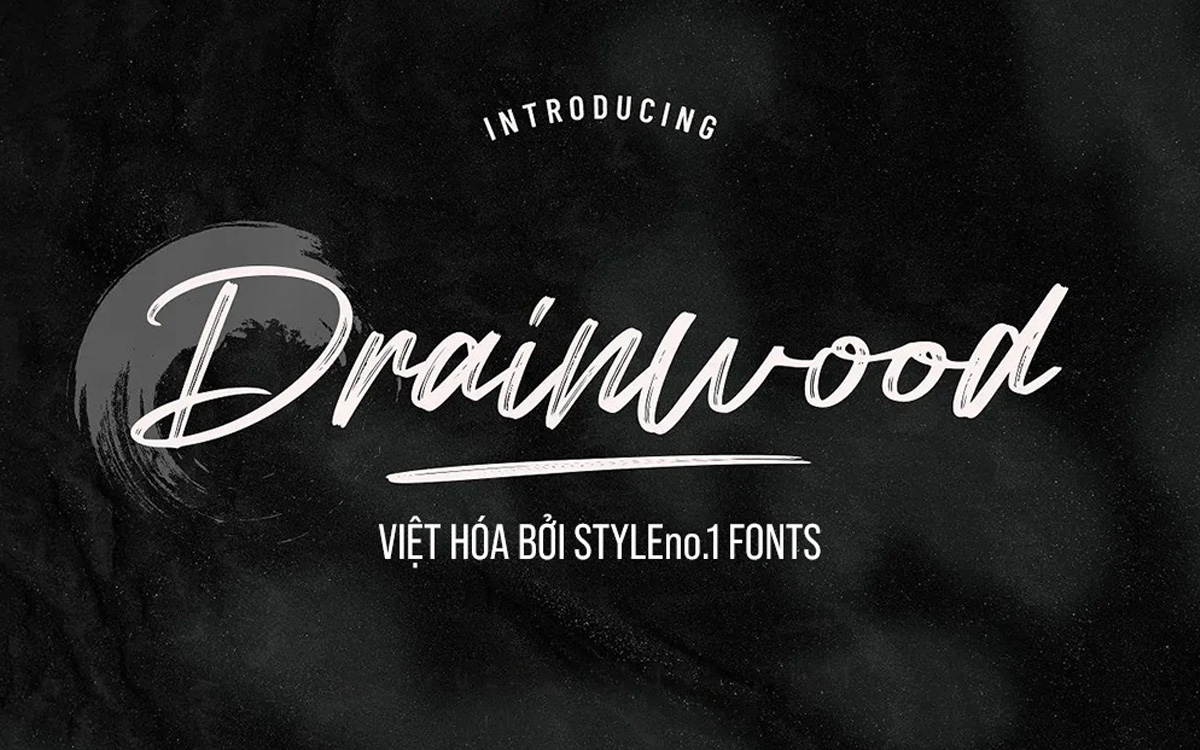
Font chữ nét cọ mềm mại viết tay SVN-Drainwood
Nếu bạn đang tìm kiếm một bộ phông chữ vừa mang phong cách nghệ thuật phóng khoáng, vừa giữ được sự mềm mại tự nhiên của nét cọ thủ công, thì font chữ nét cọ mềm mại viết tay SVN-Drainwood chính là sự lựa chọn hoàn hảo. Với các đường nét uốn lượn giàu cảm xúc cùng bản Việt hóa chỉn chu, bộ font này giúp nâng tầm những ý tưởng thiết kế truyền thông, nhận diện thương hiệu hay ấn phẩm in ấn trở nên vô cùng sống động. Hãy cùng khám phá chi tiết những đặc điểm nổi bật và tính ứng dụng vượt trội của phông chữ này ngay dưới đây.
Font Chữ Nét Cọ Mềm Mại Viết Tay SVN-Drainwood – Điểm Nhấn Nghệ Thuật Độc Đáo Cho Mọi Thiết Kế
Trong thế giới thiết kế đồ họa hiện đại, sự lên ngôi của các phông chữ viết tay (handwritten brush script) đã mang đến một làn gió mới, giúp sản phẩm truyền thông thoát khỏi sự khô khan của các hình khối truyền thống. Font chữ nét cọ mềm mại viết tay SVN-Drainwood không chỉ đơn thuần là một công cụ gõ vần mà còn là một tác phẩm nghệ thuật thu nhỏ, tái hiện chân thực từng cú nhấp cọ, từng vết loang mực nhè nhẹ của người nghệ sĩ typography. Bộ font này mang lại cho người xem cảm giác thân thiện, mộc mạc nhưng không kém phần tinh tế và sang trọng.
1. Đường Nét Cọ Viết Tay Tự Nhiên Và Giàu Cảm Xúc
Đặc trưng lớn nhất của font SVN-Drainwood chính là cấu trúc nét chữ được mô phỏng từ cọ vẽ thực tế. Các nét thanh, nét đậm được phân bổ vô cùng nhịp nhàng, tạo ra sự chuyển động thị giác mượt mà và ngẫu hứng. Không giống như nhiều bộ font script vi tính hóa khác có phần cứng nhắc, SVN-Drainwood giữ trọn vẹn sự gồ ghề nhẹ nhàng của vết mực, mang đến cảm giác chân thực, ấm áp và giàu chất thơ cho mọi tác phẩm thiết kế.
Mỗi ký tự trong bộ phông này đều được trau chuốt kỹ lưỡng để khi đứng cạnh nhau, chúng tạo nên một nhịp điệu liên kết tự nhiên như được viết ra trực tiếp từ bàn tay của một họa sĩ calligrapher chuyên nghiệp.
2. Hỗ Trợ Tiếng Việt Đầy Đủ Và Chuẩn Xác (Bản Việt Hóa Tỉ Mỉ)
Một trong những điểm cộng lớn khiến font chữ nét cọ mềm mại viết tay SVN-Drainwood được cộng đồng designer Việt Nam cực kỳ ưa chuộng chính là khả năng hỗ trợ tiếng Việt trọn vẹn. Bản Việt hóa do SVN thực hiện được tính toán kỹ lưỡng về mặt khoảng cách (kerning) và vị trí của các dấu thanh như sắc, huyền, hỏi, ngã, nặng hay các dấu mũ.
Các dấu câu tiếng Việt không bị lệch hàng, không đè lên nét chữ chính hay làm mất đi vẻ thẩm mỹ vốn có của nét cọ. Nhờ đó, bạn hoàn toàn có thể yên tâm sáng tạo các nội dung tiếng Việt dài mà vẫn duy trì tính nghệ thuật cao nhất cho tổng thể bức ảnh.
3. Bộ Ký Tự Thay Thế (Alternates) Và Nét Nối (Ligatures) Phong Phú
Để tăng khả năng tùy biến cho nhà thiết kế, SVN-Drainwood tích hợp hệ thống OpenType Features mạnh mẽ với rất nhiều ký tự thay thế (Alternate Characters), nét uốn móc (Swashes) và nét nối (Ligatures). Điều này giúp bạn dễ dàng thay đổi điểm đầu, điểm cuối của một từ, tạo ra những logo hay tiêu đề độc bản không đụng hàng.
Việc kết hợp linh hoạt các nét uốn lượn này giúp cho tác phẩm của bạn trông hoàn toàn tự nhiên, xóa bỏ hoàn toàn cảm giác lặp lại ký tự thường thấy trên các ứng dụng máy tính.
4. Khả Năng Ứng Dụng Đa Dạng Trên Nhiều Lĩnh Vực Thiết Kế
Với vẻ đẹp vừa lãng mạn, vừa hiện đại, font chữ nét cọ mềm mại viết tay SVN-Drainwood có khả năng thích ứng tuyệt vời trên đa dạng các sản phẩm thiết kế đồ họa:
• Thiết kế bộ nhận diện thương hiệu: Tạo logo, nhãn mác, bao bì cho các sản phẩm handmade, mỹ phẩm thiên nhiên, quán cafe, tiệm bánh, hay thương hiệu thời trang vintage.
• Truyền thông mạng xã hội: Thiết kế banner, poster, hình ảnh câu nói hay (quotes), thumbnail YouTube, hình ảnh bài đăng Facebook, Instagram thu hút sự chú ý nhanh chóng.
• Ấn phẩm sự kiện & Thiệp cưới: Làm thiệp mời cưới, menu tiệc, bảng đón khách (welcome board) mang phong cách rustic, mộng mơ và sang trọng.
• Bìa sách & Tạp chí: Phù hợp cho các tiêu đề sách văn học, tiểu thuyết, tạp chí phong cách sống, du lịch và ẩm thực.
5. Tương Thích Hoàn Hảo Với Mọi Phần Mềm Thiết Kế Hàng Đầu
Bí Quyết Phối Hợp Font SVN-Drainwood Để Tạo Nên Sản Phẩm Thiết Kế Ấn Tượng
Mặc dù font chữ nét cọ mềm mại viết tay SVN-Drainwood sở hữu sức hút rất lớn, việc áp dụng đúng nguyên lý thị giác sẽ giúp sản phẩm thiết kế của bạn trở nên ấn tượng và chuyên nghiệp hơn nữa. Dưới đây là một số lời khuyên hữu ích từ các chuyên gia thiết kế:
Tạo Sự Tương Phản Với Các Font Chữ Không Chân (Sans-Serif)
Vì SVN-Drainwood là một font script nét cọ uốn lượn nổi bật, bạn nên sử dụng nó cho các tiêu đề chính (Headings), từ khóa quan trọng hoặc các dòng slogan ngắn. Đối với phần văn bản nội dung (Body text), hãy kết hợp cùng các phông chữ không chân đơn giản như Montserrat, Helvetica, Open Sans hoặc Roboto. Sự tương phản giữa nét uốn lượn nghệ thuật và nét thẳng hiện đại sẽ tạo nên sự cân bằng hoàn hảo cho thị giác người xem.</p>